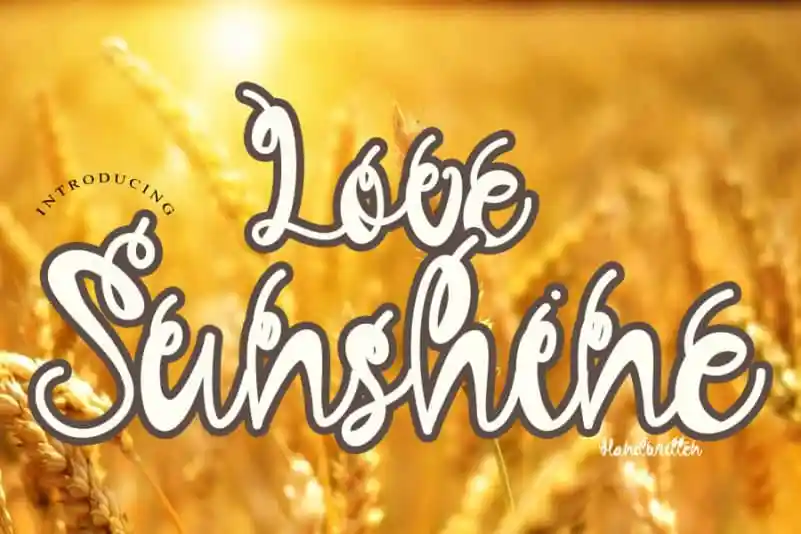
Love Sunshine Script Font – Download Grátis
A Love Sunshine Script Font é uma linda fonte escrita à mão, perfeitamente adaptada para projetos que valorizam emoções alegres e delicadas. Seu design quente, romântico e enérgico torna cada ideia um trabalho de arte realista. Com esta fonte encantadora, você pode explorar suas inúmeras variações e ter funções criativas sem fim. Ideal para projetos que valorizam um tom alegre e delicado, Love Sunshine Script é uma escolha perfeita para quem busca uma fonte escrita à mão que seja tanto versátil quanto encantadora. Experimente e descubra por si mesmo as possibilidades inúmeras de uso dessa linda fonte.